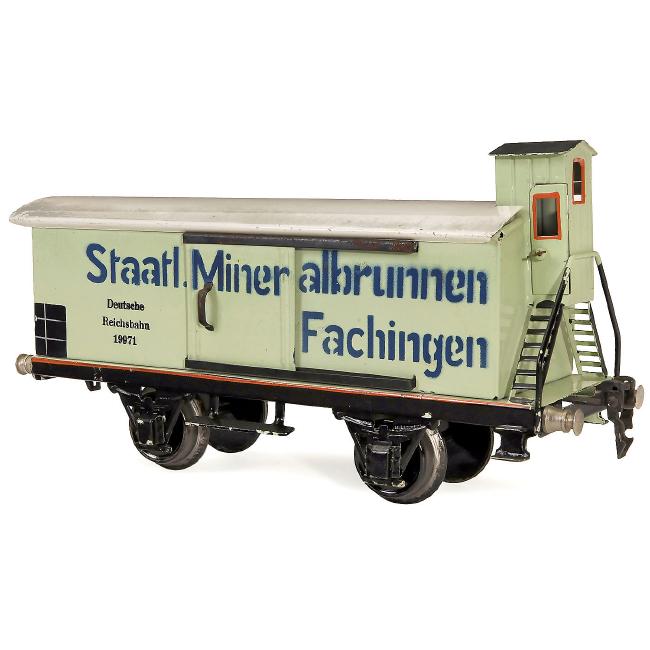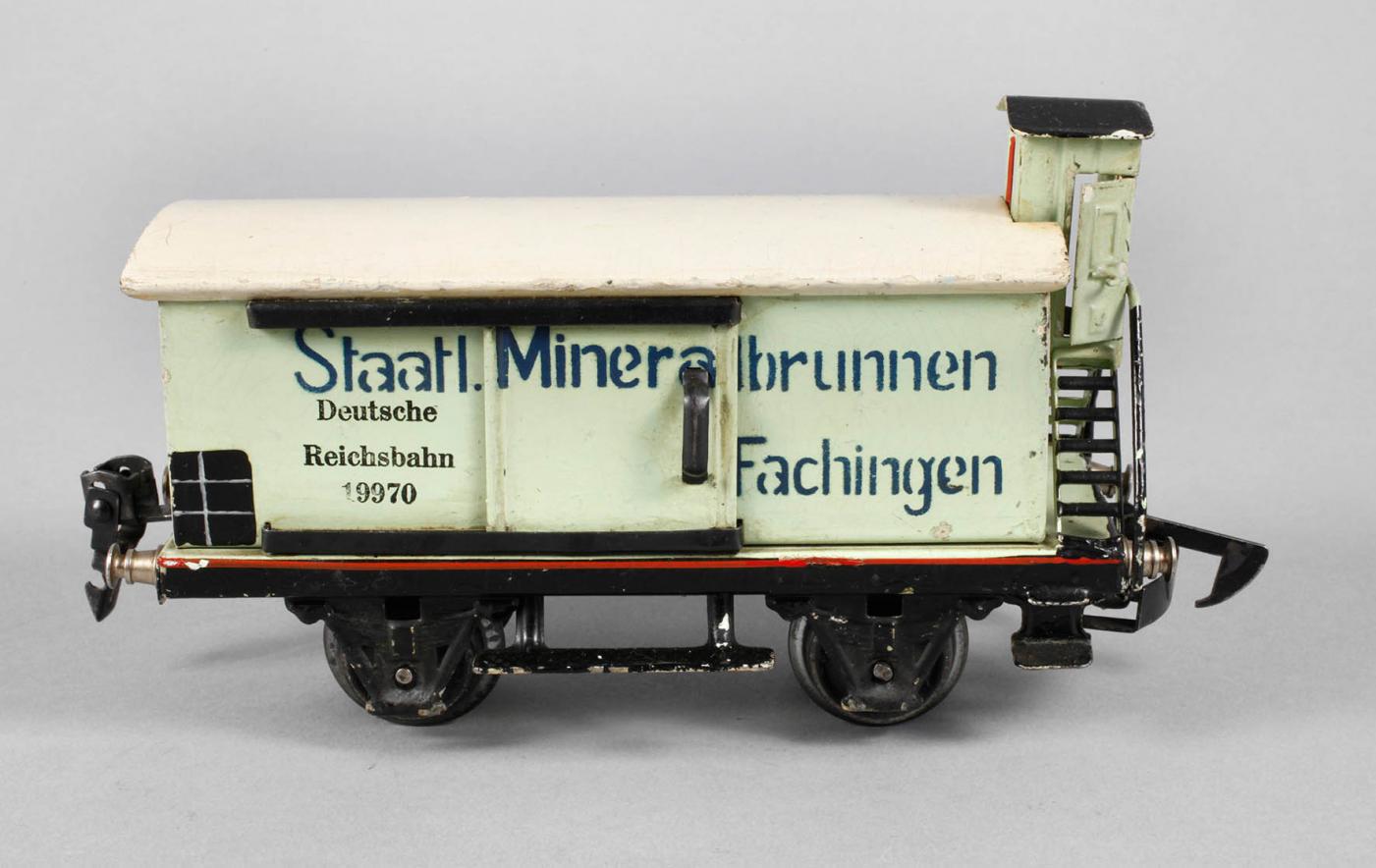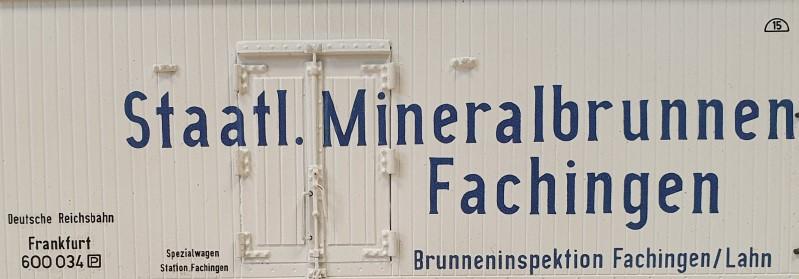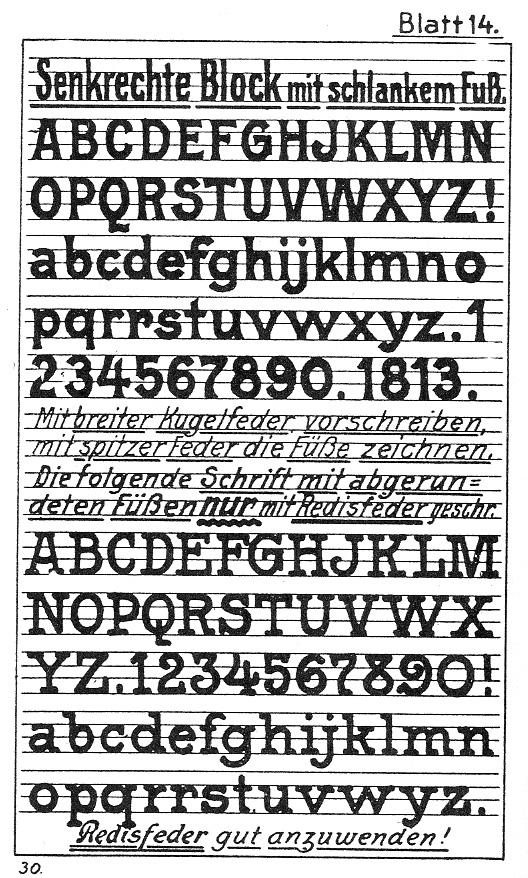
Schriftart Staatlich Fachingen aus den 20iger Jahren gesucht
bei einer Recherche im Netz bin ich auf dieses Forum gestoßen. Vielleicht kann mir ja hier jemand helfen.
Für die Gestaltung eines Modellgüterwagen aus den 20 iger Jahren benötige ich Hilfe bei der Identifikation der verwendeten Schriftart. Meine Suche war bisher erfolglos.
Hallo @Holger66, was genau zeigt die Abbildung? Ist das eine Aufnahme des Originalwagens oder ihrerseits eines Modells?
Generell: eine Bahnbeschriftung in Schaugröße aus den 1920ern basiert mit größerer Wahrscheinlichkeit nicht auf einer Satzschrift, sondern auf Schildermalerkenntnissen (das heißt, es handelt sich um Lettering).
Vielleicht wurden die auch mit Schablonen beschriftet – zumindest deuten originale Modellbahn-Wägen mit unterschiedlichen Schriftarten aus den 30er-Jahren darauf hin, die aber alle eine Schablone wiedergeben:
Spritzschablonen am Modell: das kann auch fertigungstechnische Gründe haben wie Kosten, verfügbare Technologie (Tampondruck, ...) und muss nicht unbedingt eine Reproduktion des Originals sein. Vor allem Bild 1 zeigt eine schlampige Ausführung. Im Original hätte der Auftraggeber vermutlich auf Nachbesserung bestanden.
Gibt es auch Originalfotos dieser Waggons?
Mich hat gewundert, dass beide unterschiedliche Beschriftungen eine Schablone verwenden und denke, dass das der Originalbeschriftung entsprechen könnte.
Das Bild aus meinem ersten Beitrag zeigt einen Modellgüterwagen. Ist aber eine andere Spurweite.
Ich hatte schon Kontakt mit Staatlich Fachingen, dort weiss man leider auch nicht welche Schriftart das war.
Bilder aus den 20 iger Jahren habe ich keine gefunden.
Ich habe schon diverse  Schriften geprüft und immer gab es irgendwo eine markante Abweichnung.
Es handelt sich wahrscheinlich um eine Schrift, die nach einer Schildermalervorlage aufgebracht worden ist. Hier mal ein recht ähnliches Beispiel aus diesem Fakismile.*
Gibt es diese Schrift auch als Font? Ggf. auch kostenpflichtig?
Nun, da damals all diese Anschriften von Schildermalern gemacht wurden, können die auch kaum sagen, wie die Schrift hieß, denn sie hatte sehr wahrscheinlich auch gar keinen Namen, als dass die dem Schildermaler eben gesagt haben: Zeichne uns eine Blockschrift... Aber das sagte man damals praktisch zu jeder Grotesk-Schrift.
Ich würde hier eher bei Fachingen noch mal fragen, ob die von diesen Anschrtiften irgend welche original-Abbildungen aus der Zeit haben. Dann würde ich mich auch gern daran machen, eine "Fachinger Block" zu bauen. Modellbahn-Schriften habe ich ja schon einige gebaut, und auch grad so etwas in Arbeit.